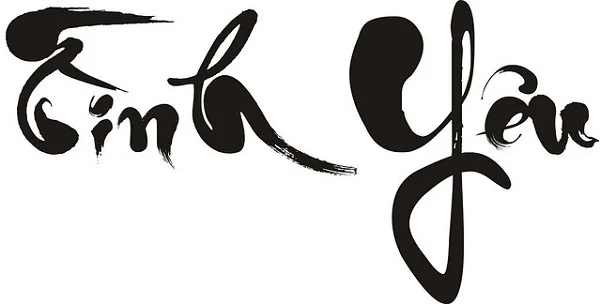
Hiện nay, font thư pháp được ưa chuộng và sử dụng rất nhiều phục vụ cho nhiều mục đích khác nhau như thiết kế, viết câu đối hay tạo chữ ông đồ,... Font thư pháp hay còn được biết đến là font ông đồ với những đường nét chữ được viết phá cách, sáng tạo. Font thư pháp được nhiều người trong dân gian ví là nghệ thuật chữ rồng bay phượng múa. Chính vì, sự phá cách, sáng tạo và độc đáo của font thư pháp việt hóa này mà font chữ này được ứng dụng rất nhiều trong các sản phẩm thiết kế. Tuy nhiên, font thư pháp không phải tùy ý sử dụng mà còn tùy vào từng hoàn cảnh và mục đích sử dụng sao cho phù hợp với văn hóa. Dưới đây là những thông tin cần biết về font thư pháp việt hóa cũng như link tải miễn phí font thư pháp việt hóa đẹp, sáng tạo nhất, cùng tham khảo bài viết dưới đây nhé!
Font thư pháp là font chữ có các đường nét viết dày mảnh khác nhau. Hiện nay, font thư pháp gồm có rất nhiều kiểu font chữ khác nhau, người dùng có thể thoải mái lựa chọn font chữ phù hợp với thiết kế của mình. Những nét mực được tạo ra từ các phông chữ thư pháp có nét mực giống với nét mực viết chữ lên giấy mà các ông đồ thường viết tặng chữ. Những mẫu font chữ thư pháp có phong cách riêng biệt, độc đáo và sáng tạo những nét chữ viết được ví như rồng bay phượng múa. Vì vậy, font chữ thư pháp việt hóa này rất thích hợp để thiết kế những tác phẩm nghệ thuật đẹp mắt.